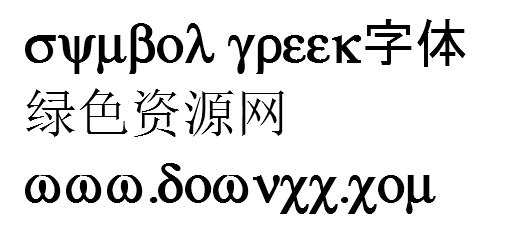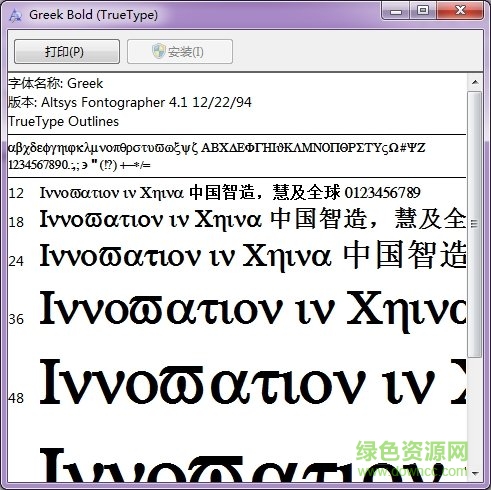
symbol greek
symbol greek字體是一款希臘字體,幫助設(shè)計(jì)師更好的輸入和顯示希臘文字,中文字體是正常的黑體格式,英文字體都將轉(zhuǎn)換成希臘字母,如果你有需要,請(qǐng)來綠色資源網(wǎng)下載吧!
greek字體特色
symbol greek是將我們熟知的英文字母全部用希臘字母表達(dá),而中文漢字不變,是用來設(shè)計(jì)希臘文字時(shí)的好工具,可以適用在平面設(shè)計(jì)、廣告設(shè)計(jì)等多種場(chǎng)合。
如果是排現(xiàn)代希臘文,要考慮字體對(duì)字符集的支持程度,因?yàn)椴⒎撬械淖煮w都支持希臘字母。除了普通的希臘字母,還要有一些加附加符號(hào)的字母,一般需要字體支持 Unicode 中「希臘文和科普特文」中的希臘文部分。如果是排多調(diào)希臘文,還需要支持 Unicode 中「希臘語擴(kuò)充」部分。但是,多調(diào)希臘文中有時(shí)還需要一些 Unicode 中尚未收錄的、帶更多附加符號(hào)的字母,比如一些古希臘語教材中會(huì)用到,那就需要更專業(yè)的字體,這種字體一般是把這些字符放到「私用區(qū) / 專用區(qū)」里的,可以通過 Open Type 的連字功能轉(zhuǎn)換出來,當(dāng)然也可以簡(jiǎn)單粗暴地用它的 Unicode 編碼來輸入(因?yàn)槭撬接脜^(qū),需要先了解這個(gè)字體是怎樣給這些字符分配編碼的)。